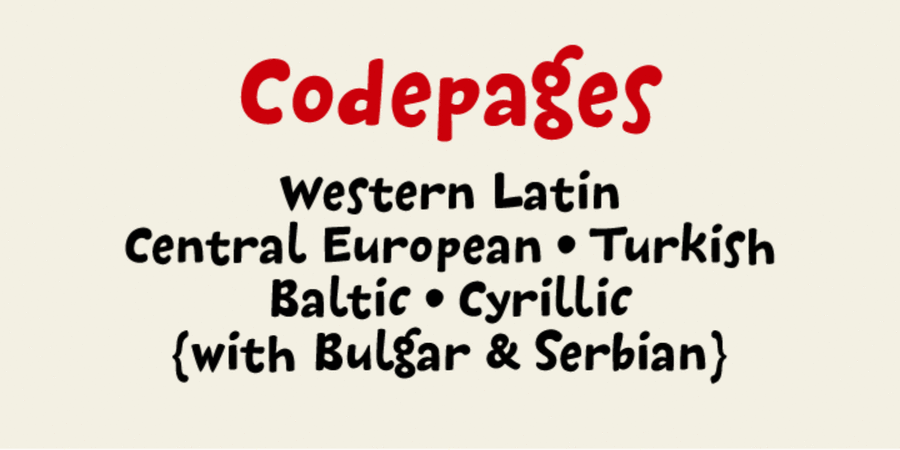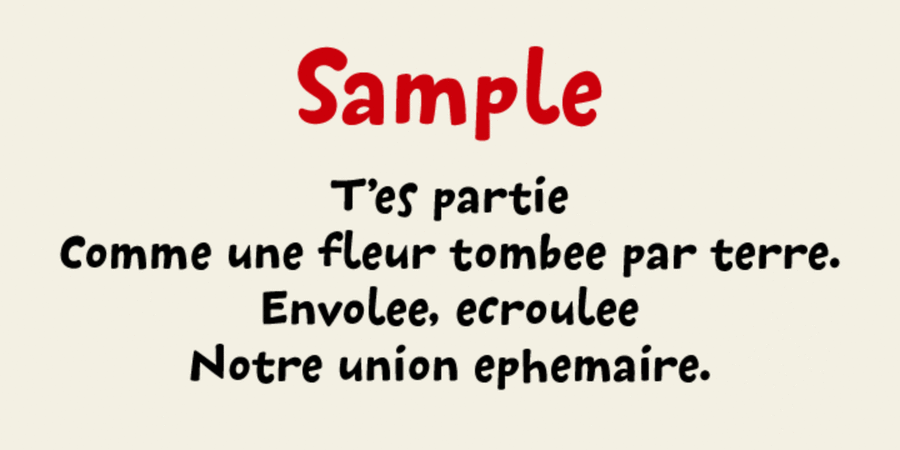
Шрифтова пара з CoolKids Light (1 з 6)Опис шрифта DR Galushki HoleГалушки – це м'який добрий і жартівливий шрифт. Він ідеально підходить для коміксів, іграшок, дитячих книжок, упаковки та реклами. Шрифт розробив Дмитро Растворцев у 2005-2010 роках.
Асоціації з сімейством шрифтів DR Galushki HoleОсобистість і характер гарнітури:
стрибучий, привітний, веселий, задерикуватий, смішний, доброзичливий, добродушний, добрий, радісний, неохайний, грайливий, пустотливий, непосидючий, рухливий, оригінальний, свіжий, стиглий, смачний, М'який, простодушний, наївний, дитячий, мультяшний, святковий, динамічний, карикатурний, милий, дотепний, домашній, літній, щасливий, прикольний, симпатичний, фруктовий, ягідний, соковитий
дитяча книжка, олівці, табір, фломастери, пластилін, гумор, анімація, сніданок, іграшка, дитяче харчування, їжа, свято, соус, фаст фуд, закуска, морозиво, кондитерська, солодощі, випічка, булочки, булочна, молоко, сметана, галушки, вареники, зоопарк, клоун, розфарбування, хенд мейд, гра, зоомагазин, тварини, відпочинок, школа, м'яка іграшка, мультфільм, прикраса, дитсадок, дитячий ранок, котики, канікули, шоу, телебачення, десерт, смузі, жуйка, підгузок, фрукти, мармелад, сік, сир, графіка, ілюстрація, дім, ранок, малюк, собачка Гарнітура асоціюється з віком: